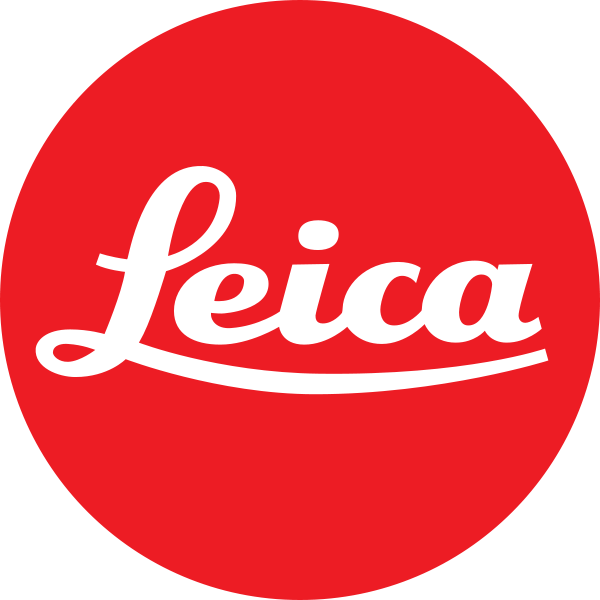
Suche die Schrift von dem alten Leica Logo in dem roten Kreis
Ich seh’ kein Logo …
Das ist eindeutig ein Logo, dass noch aus einer Zeit stammt, in der kein Grafiker sich zu einem Setzer bemüht hat, um einen Logo-Schriftzug sich erst einmal in Blei setzen zu lassen, oder eben die Buchstaben auf einem Schrift-Musterbuch ab zu pausen. So etwas wurde damals noch frei aus dem Handgelenk gezeichnet. Nicht selten waren allerdings solche Wortmarken eine Inspiration für Schriftgestalter, die daraus dann eine komplette Schrift entwickelten. Heute geht ja der Trend zu: Man nehme eine Schrift, Schneide da von vielleicht ein paar Ecken weg oder verbiege ein paar Bögen, und habe ein tolles Logo.
Und dann lese ich allerorten: Wie heißt die Schriftart, welche für dieses Logo verwendet wurde, obwohl hier genau umgekehrt ein Schuh draus wird: Wie heißt das Logo, nachdem diese Schriftart entwickelt wurde...